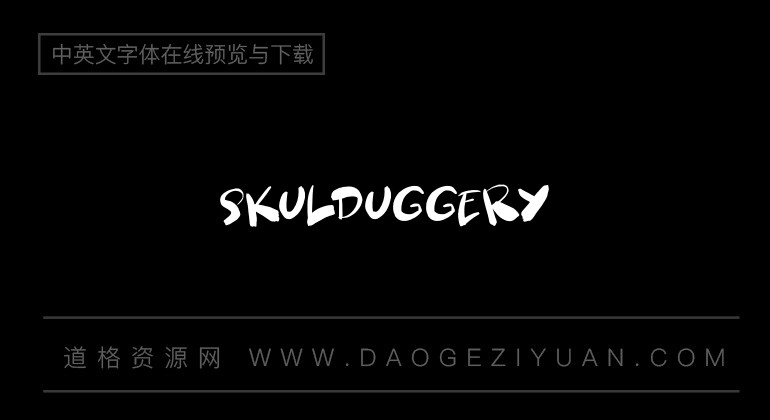
Skulduggery 是一种手写风格的无衬线字体,由美国设计师 Typodermic Fonts 制作。它的字体风格独特,具有很强的个性和动感,非常适合用于海报、广告和标志设计等场合。 Skulduggery 字体包括两种字重:常规和粗体,每种字重都包括大写字母、小写字母、数字和标点符号。它的笔画非常有特点,字母之间的连笔非常流畅,看起来非常美观。此外,它的字母具有一些轻微的变形和曲线,使得整个字体看起来更加生动有趣。 总的来说,Skulduggery 是一款非常富有个性的手写字体,适用于很多不同的设计场合。如果您正在寻找一款独特的字体来吸引人们的注意力,那么 Skulduggery 可能会是一个不错的选择。内容介绍
Skulduggery是一款非常不错的手写艺术字体,具有很好的视觉感,适合于文化类的宣传设计、商业类品牌的广告和产品包装设计以及个性化文字排版等较多场景。